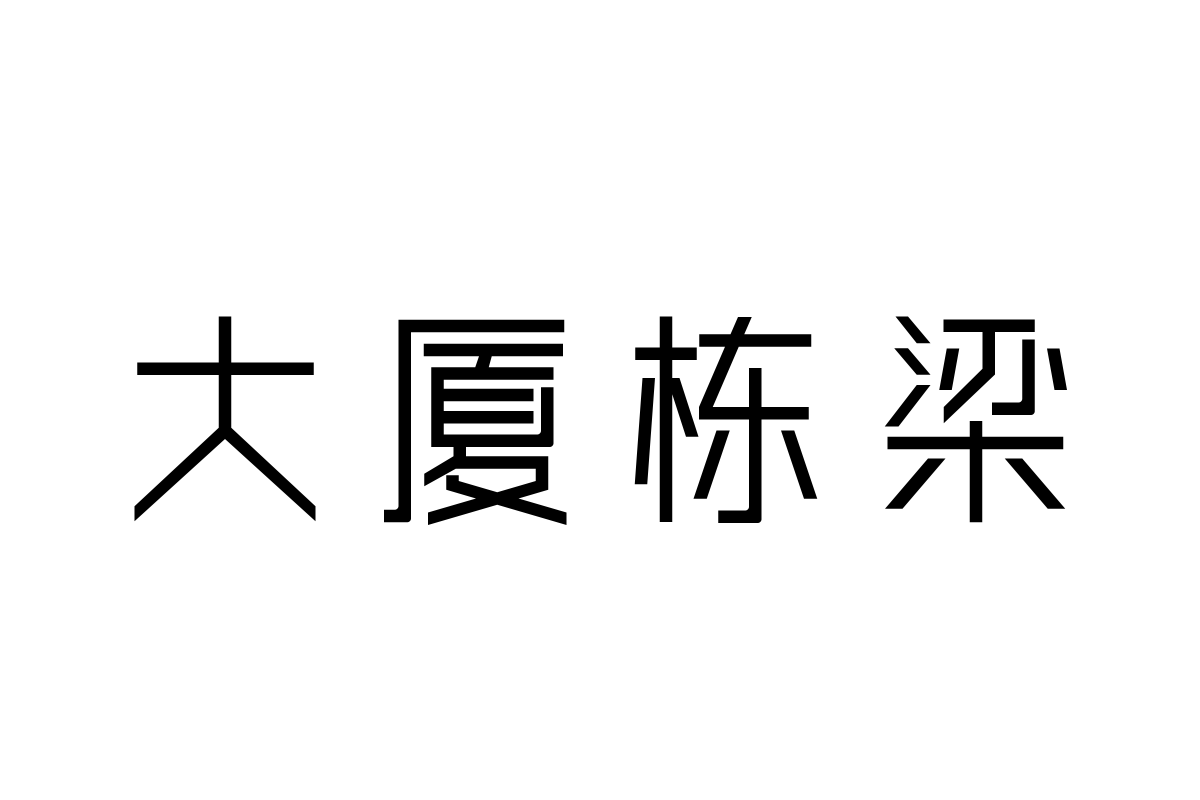
三极新雅细黑简体是一套由三极公司开发的中文字体,旨在为用户提供高质量的文本排版体验。该字体以其独特的设计和风格脱颖而出,具有以下特点:
1. 简洁优雅:三极新雅细黑简体采用了简洁的线条和优雅的字形设计,使得文字在视觉上呈现出一种简约而不失美感的效果。
2. 清晰易读:该字体具有良好的可读性,适用于各种场景,如书籍、报纸、杂志等,确保读者能够轻松阅读。
3. 适用范围广泛:三极新雅细黑简体适用于多种应用场景,包括网页、桌面软件、移动应用等,满足不同用户的需求。
5. 易于使用:三极新雅细黑简体提供了丰富的字重选择,用户可以根据自己的喜好选择合适的字重,以满足个性化需求。
总之,三极新雅细黑简体是一款功能强大且实用的中文字体,适合各类文本排版场景,为用户带来优雅的视觉体验。